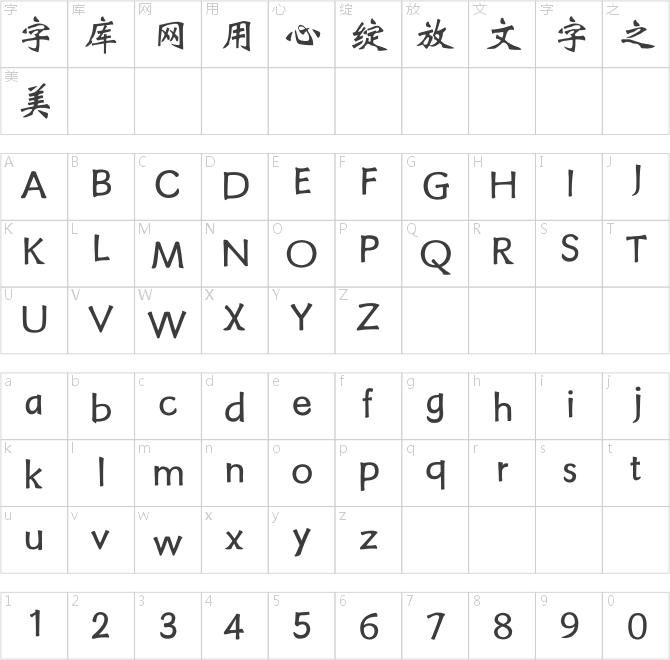
字體名稱: 點(diǎn)字仙俠體
點(diǎn)字仙俠體字體字庫(kù)是一款讓人賞心悅目、百看不厭的中文字體,適合各類廣告和產(chǎn)品包裝設(shè)計(jì)應(yīng)用,字體大小6.52MB,格式為ttf字體,上傳用戶是程玉玲,作者/版權(quán)方為點(diǎn)字庫(kù)/字由